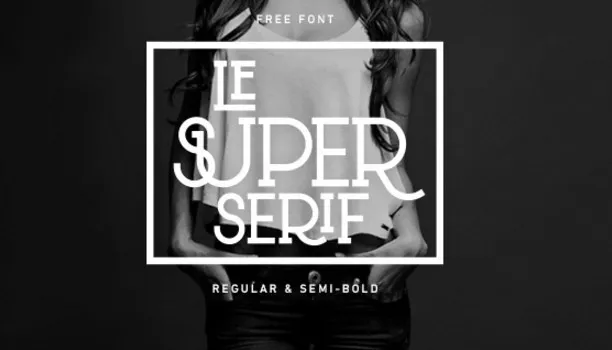
Le Super Serif Font – Fonte Grátis
Le Super Serif Font
Estou aqui a fonte perfeita para dar ao seu projeto uma aparência contemporânea e sofisticada sem perder o charme clássico dos serifos. Introduzimos Le Super Serif Font, um tipo de letra com cara moderna que mantém o encanto tradicional da serifada. Desenhado pelo designer Hamilton que também vem do Rotterdam, Holanda, a fonte leva uma mistura elegante entre os padrões europeus e o estilo atual. Com 88 ligaturas inclusas, dá ao seu texto um toque de modernidade e alguns caracteres alternativos “especiais” para aqueles momentos em que você quer dar um tom ainda mais personalizado aos seus projetos. A fonte vem nas duas versões de peso: Regular e Semi-Bold, garantindo que encaixe perfeitamente com qualquer estilo de projeto. Le Super Serif é uma opção ideal para aquelas criações que valorizam tanto a modernidade quanto o clássico. Não deixe essa fantástica fonte passar por você!